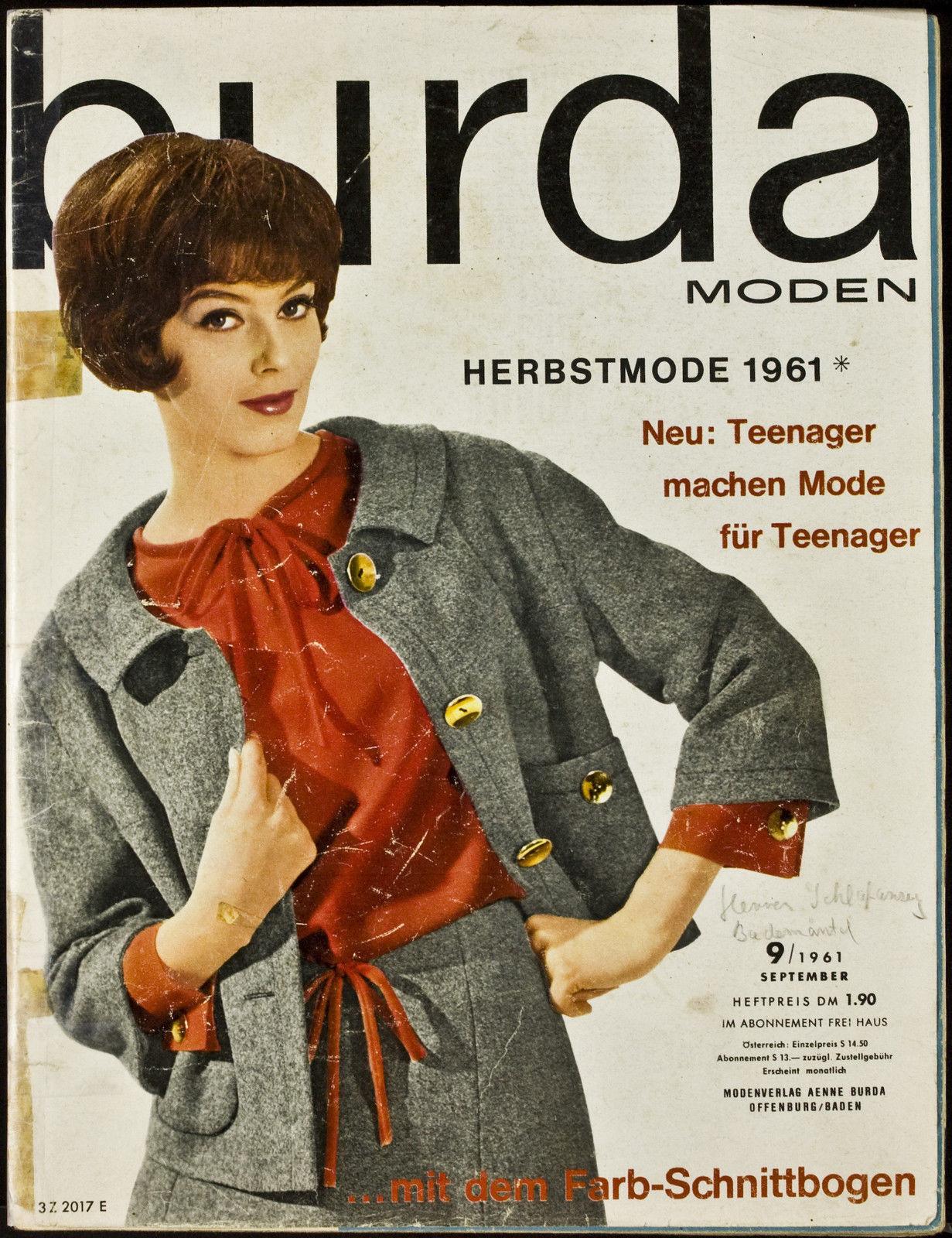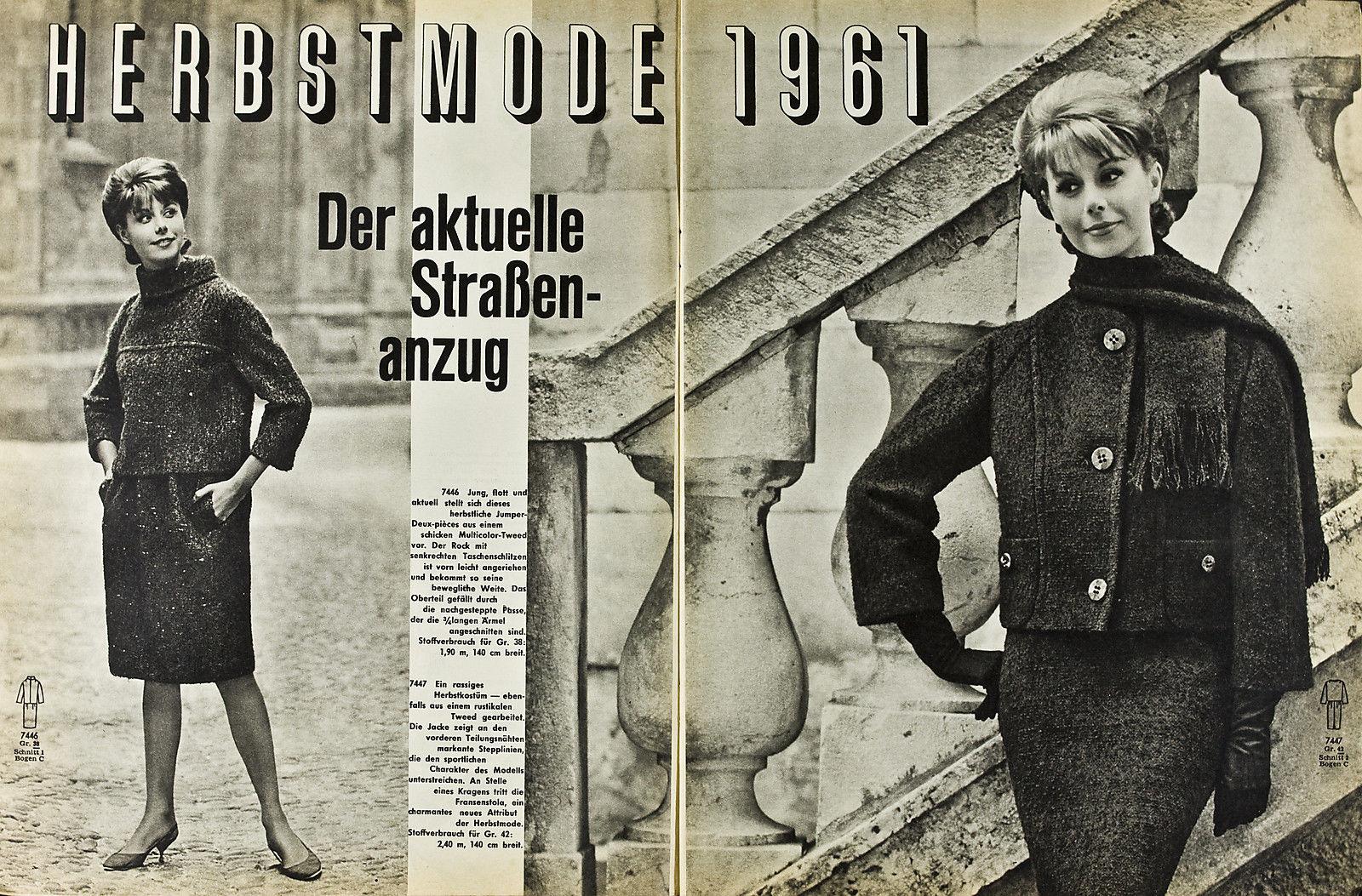
Schrift aus Werbung Anfang 60er
ich hab hier 2 Heftscans aus ner 60er Jahre Modezeitschrift: Auf Bild 1 z.B. "Teenager machen Mode für Teenager": ich dachte das wäre die UNIVERS-schrift, aber ich bin mir nicht ganz sicher.
Bei Beispiel 2 der Text "Der aktuelle Straßenzug", das ist auf jeden Fall kein UNIVERS, das erkenne ich am "a". Welche Schrift könnte das sein?